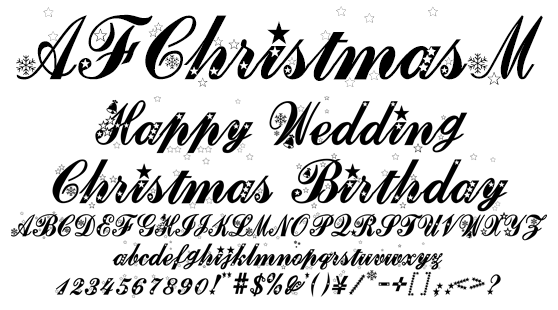
アンティークな筆記体 AFChristmasM
AFChristmasM
ファッション系ドキュメントに最適なAFChristmasのウエイトを太めにしてデコレーションを変更。クリスマスやバースデーに利用できるフォントです。動画テロップ、Web Server へのアップロード、フォント共有サーバー利用、PDF エンベッド、印刷やロゴなど作成と登録、印影や彫刻、画像化後ソフトへのバンドルなど商用利用できます。